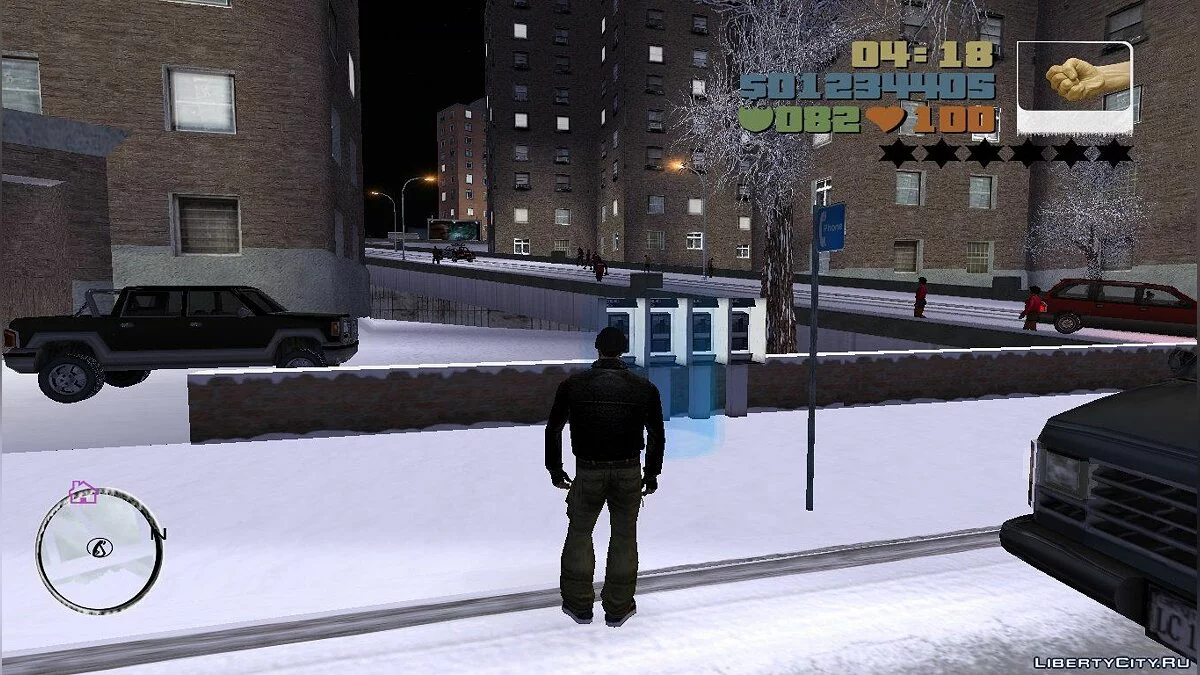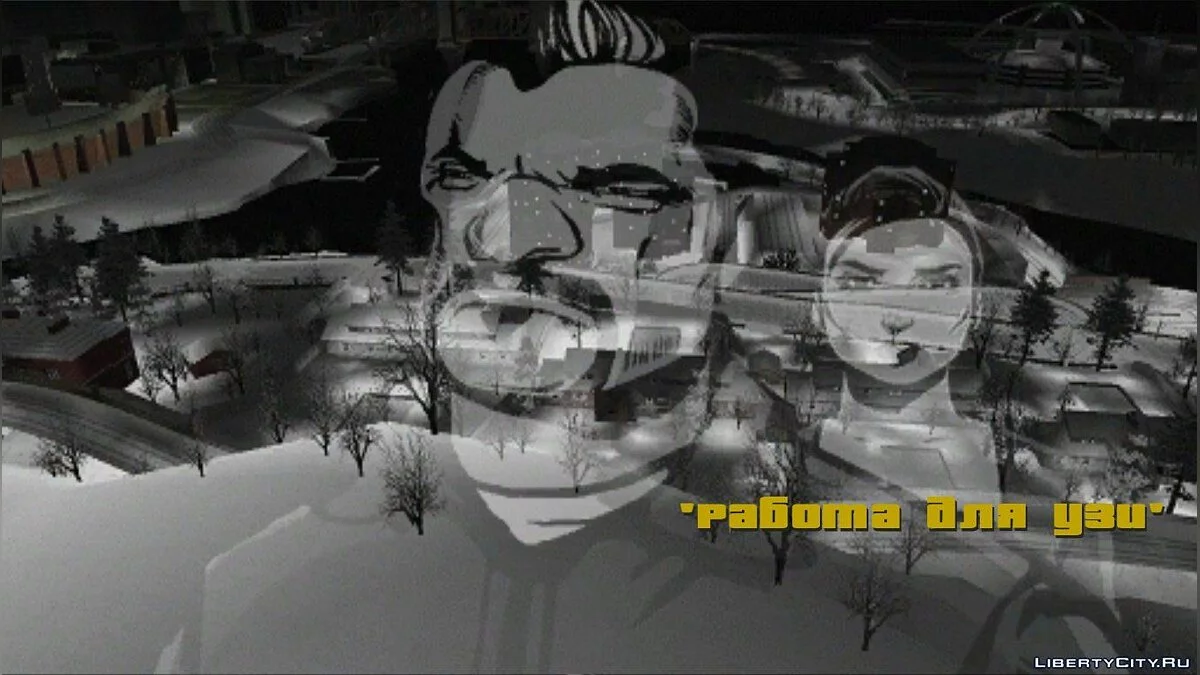
OnePiece GTA 3 HD Font v1.2
Все, возможно, уже видели новый HD шрифт от OnePiece, верно? И многих огорчил тот факт, что шрифт только на английском. Но этот мод исправляет данный факт! Теперь, присутствует и русский язык, и с этим шрифтом можно играть в GTA 3 с переводом от Буки. Так же, помимо добавления русского языка, здесь была изменена единичка (теперь, вместо какой-то палки из шрифта OnePiece здесь та самая единица, но в HD) а так же - HD-сердечко и HD-броня.